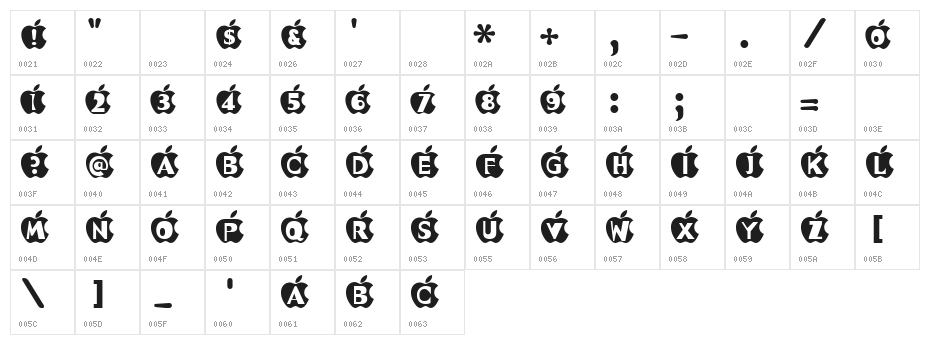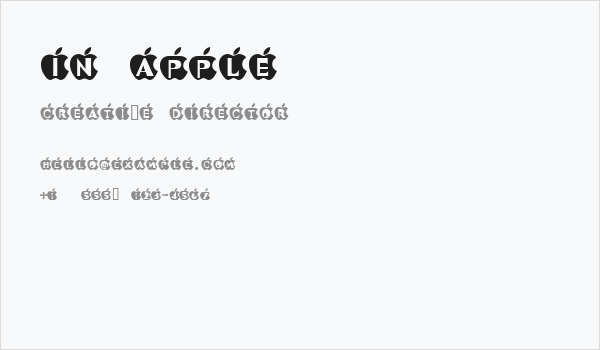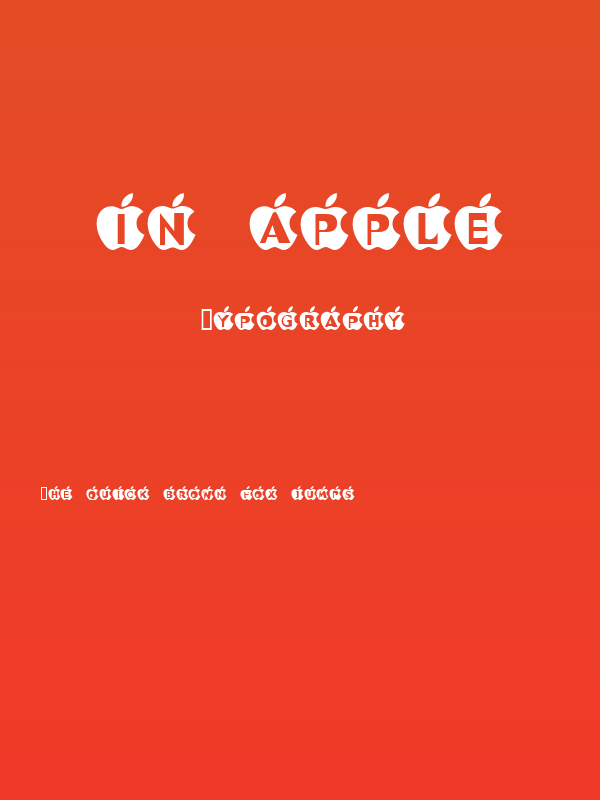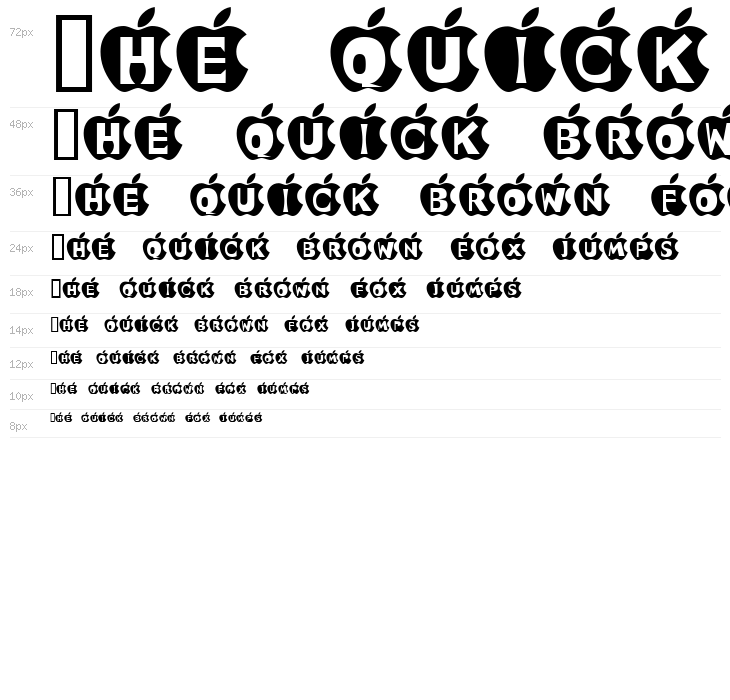
IN APPLE Font
| Stil general | Modern, Playful |
| Proiecte propuse | Ideal for children's book covers, educational materials, playful branding, and promotional materials for events or products related to technology or fruit. |